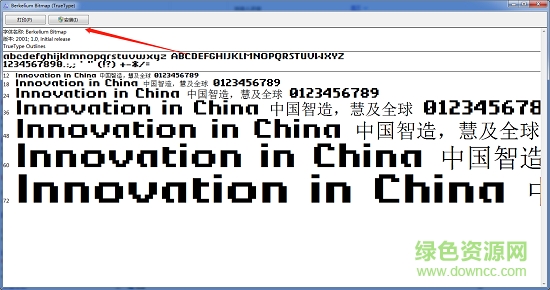
Berkelium Bitmap字體是一款非常經(jīng)典的電腦硬筆排版字體,此款字體在線條的修飾上游刃有余,可圈可點(diǎn),讓整個字體看起來既有特色,也有美感,適用于多種地方,讓用戶在字體的使用中展現(xiàn)更多不同的特色,喜歡就來綠色資源網(wǎng)下載吧!
Berkelium Bitmap字體是一款英文設(shè)計字體,此款字體設(shè)計為像素字體,專門為方便用戶打造更多你喜歡軟件的不同排版,讓用戶可以在使用中用于更多不同的特色,同時還有各種精彩等你來體驗!